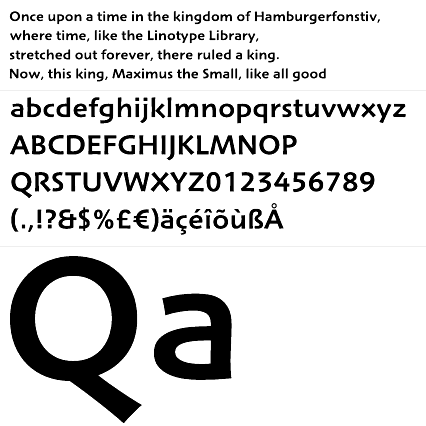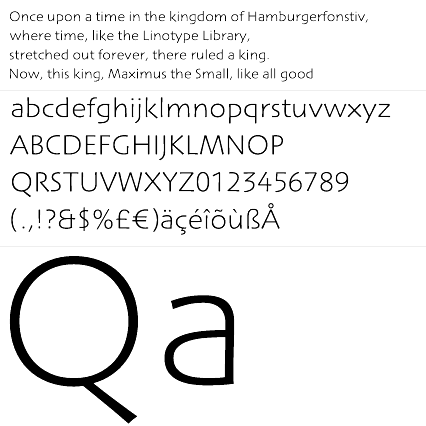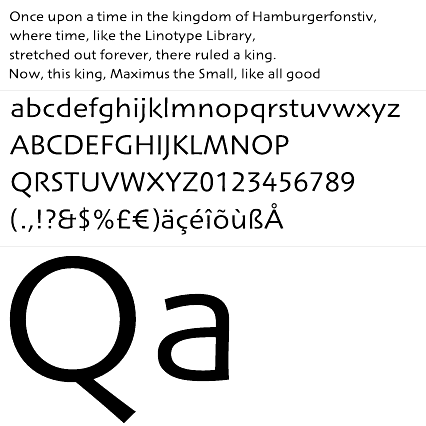
巨匠書体デザイナー Adrian Frutiger 氏とライノタイプ社・タイプディレクター 小林章氏制作:新登場
書体デザイナーの Adrian Frutiger 氏といえば Univers や Frutiger などのサンセリフ書体のデザインで知られていますね。
まだまだ現役活躍中の Frutiger 氏、ここ数年の代表的な商品といえば、プラチナ製品 Avenir Next 、Frutiger™ Capitalis フォントもメールマガジンで紹介しているのでご存知の方が多いかと思います。今回もまた新しく誕生した Nami™ 書体をご紹介致します。
Desinged by Adrian Frutiger and Akira Kobayashi, 2006
Nami フォントの原型は、1980年代にフルティガー氏がライノタイプに提案していて保留になっていた2つの新書体でした。私が過去の書類の中からその2書体を見つけて、双方の良いところを合わせてひとつの新書体にすることを考えて、2005年にフルティガー氏と打ち合わせて制作に踏み切りました。数字や記号類などはフルティガー氏にスケッチを新たに描き起こしてもらったのですが、制作の途中の段階では、フルティガー氏の提案から新しい小文字のデザインなども生まれました。
Nami のデザイン的な特徴は、有機的で柔らかい曲線で構成されている点と、空間をゆったりとっている点ですが、それだけでなく、OpenType の利点を生かして小文字のうち数文字をオルタネート文字にとりかえて文章組の表情を変えることができるという新しい機能も備えています(その機能を活かすためには OpenType に対応したアプリケーションが必要です)。
一見普通のサンセリフ体ですが、よく見ると直線部分は少なく、大文字の水平線や垂直線にはごくわずかに「しなり」を持たせてあります。小文字 a, d, g などのデザインは、かなり単純化されているのに微妙な曲線でバランスをとっているので、単純化されたサンセリフにありがちな冷たく機械的な感じがありません。ほんわか暖かい、春の海のように穏やかなサンセリフ書体です。
アドリアン氏と章氏が書体について話をしている様子
デザイン段階のスケッチ
初期スケッチ
上記のようなアンシャル体を描いたスケッチ、最終的には使用されず。